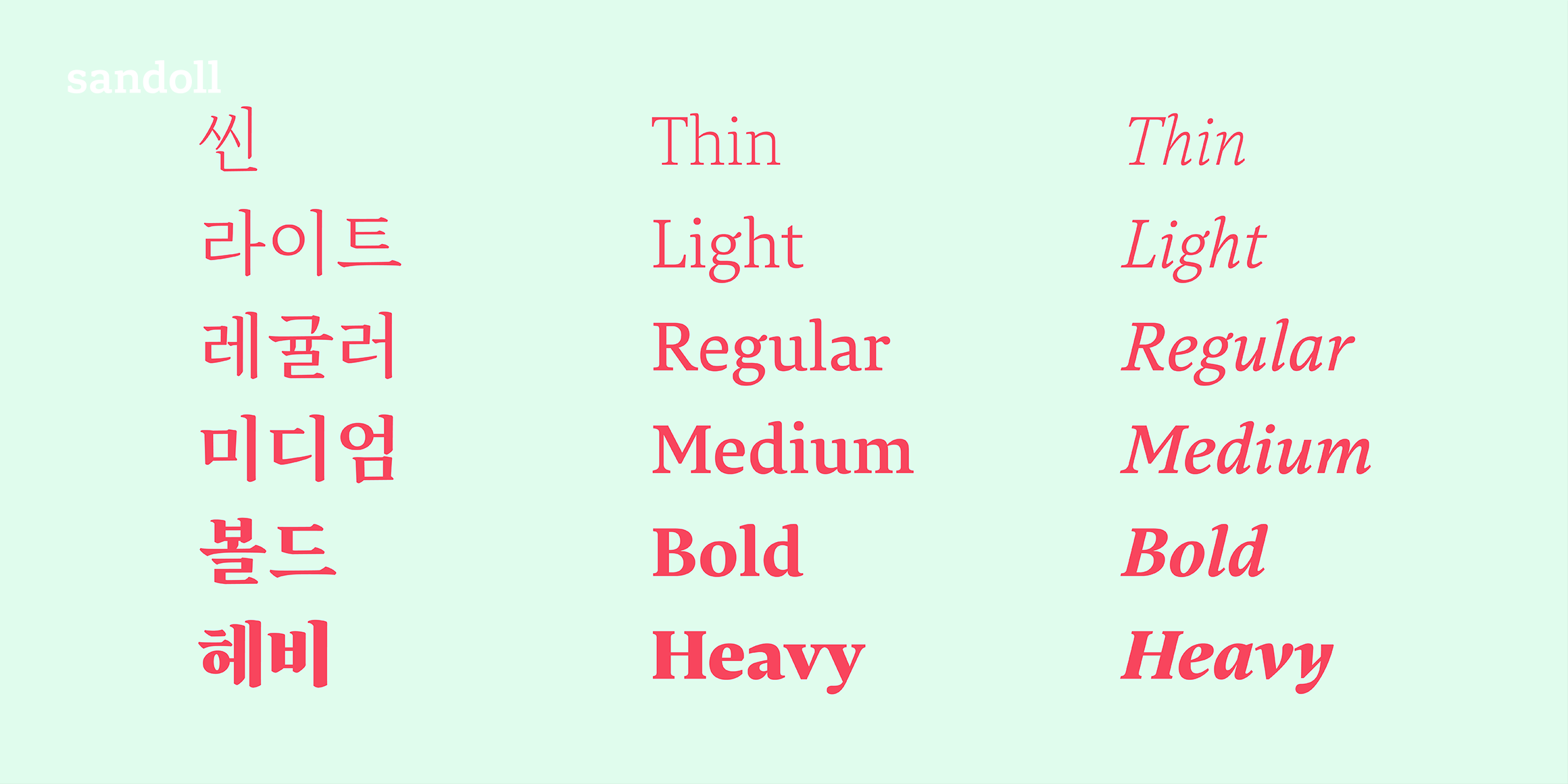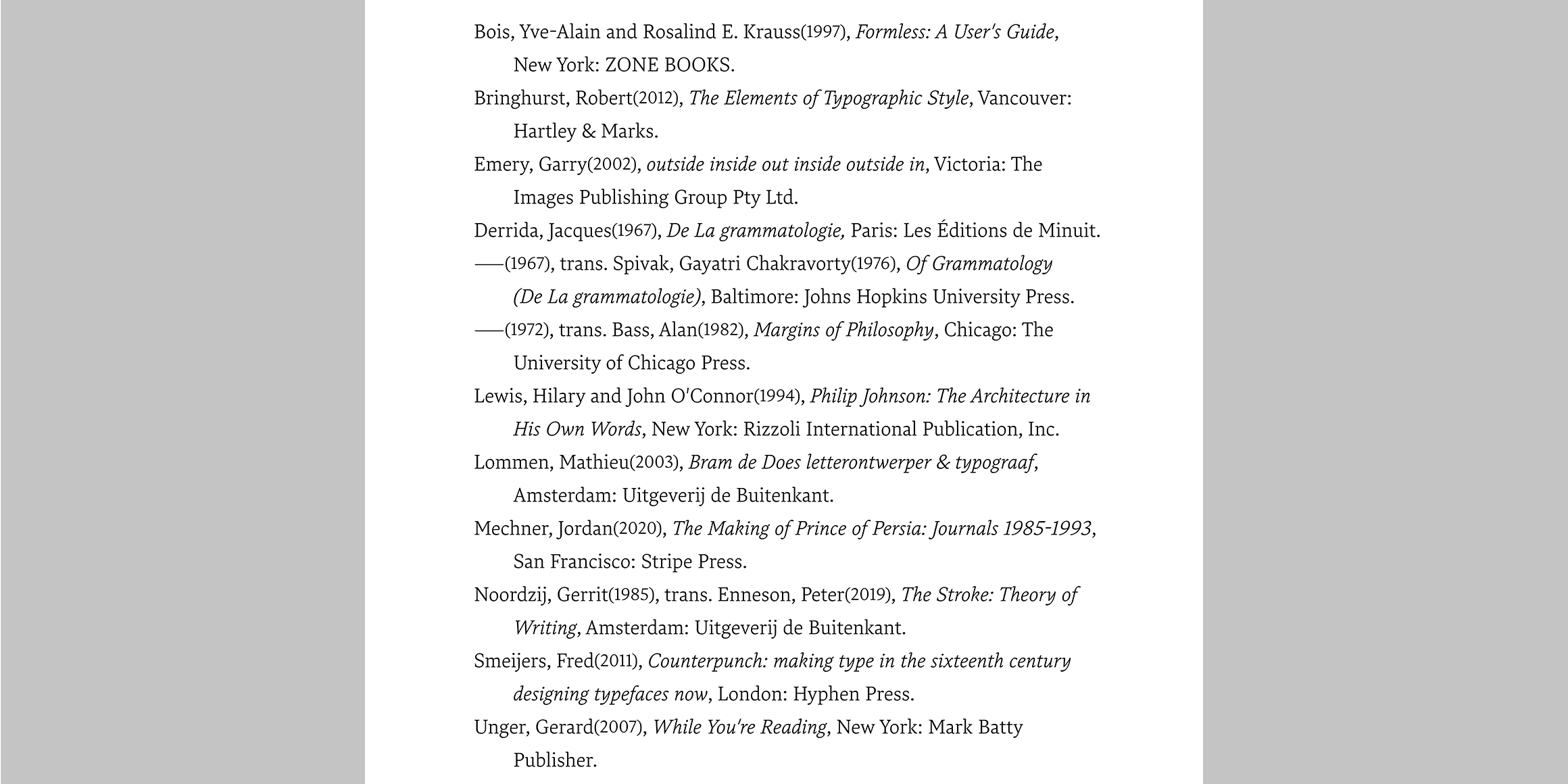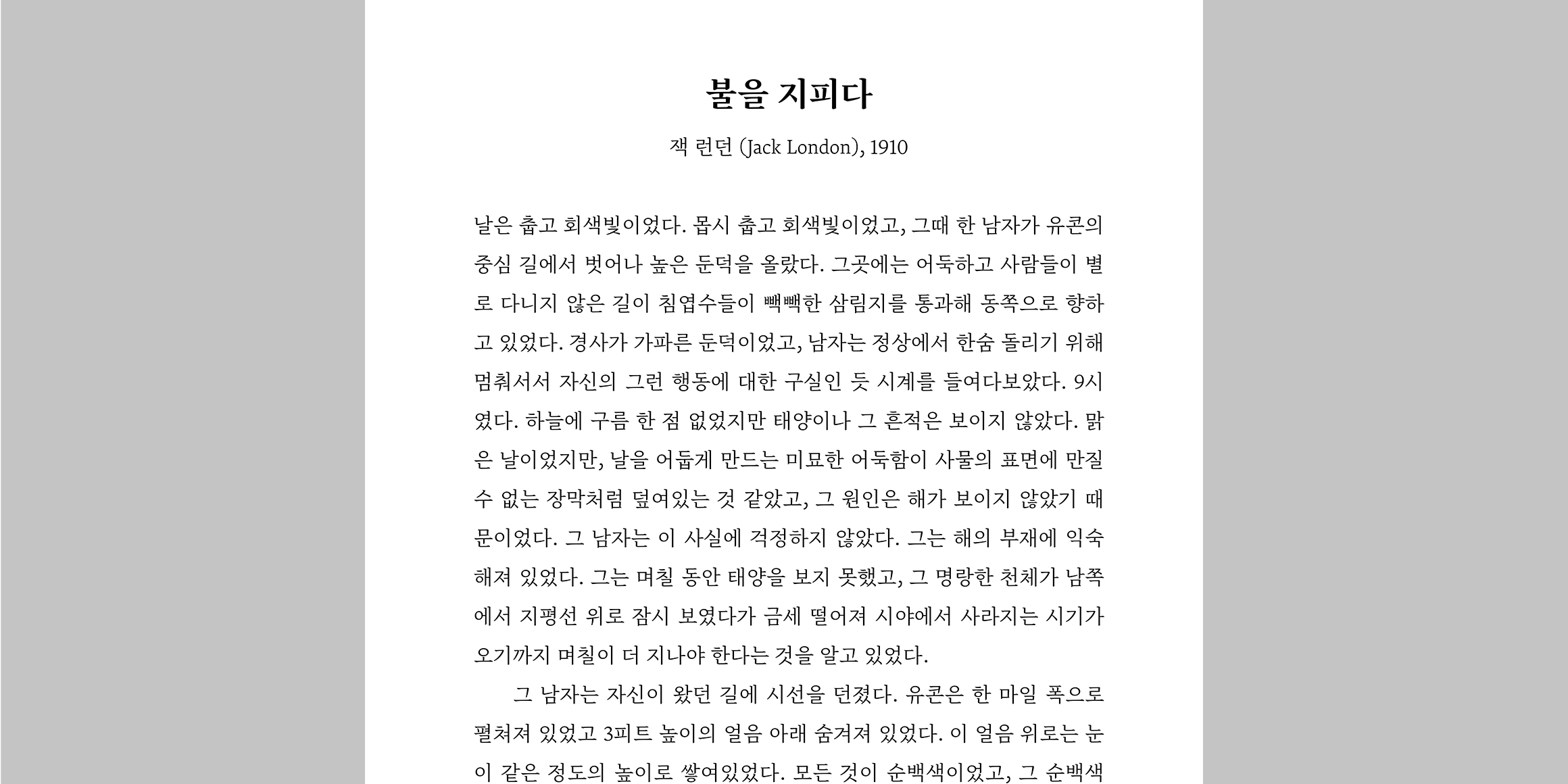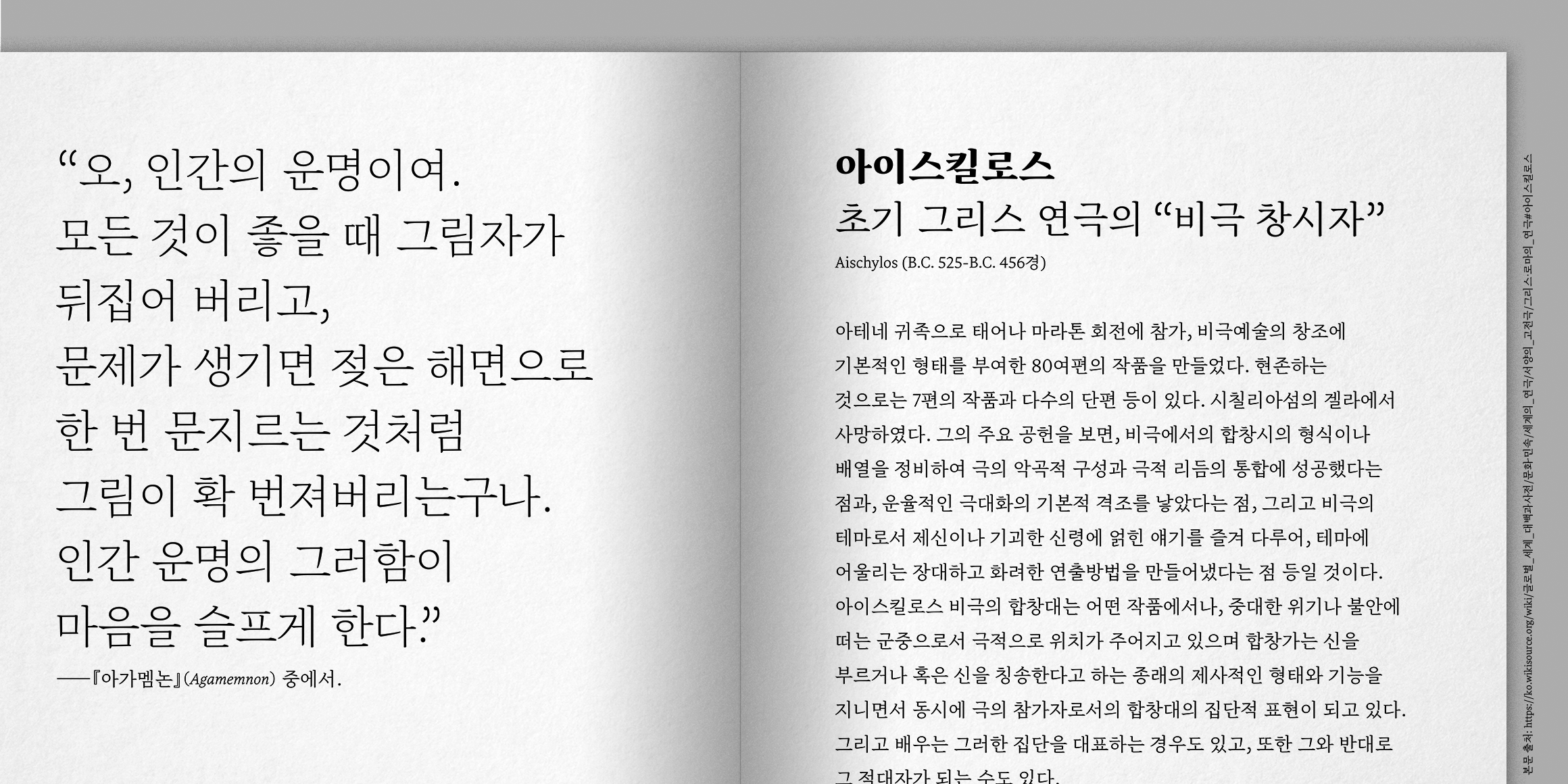
6개의 웨이트와 각 웨이트에 해당하는 이탤릭이 있고 쓰임새에 따라 골라 쓸 수 있습니다. 9-10pt 정도로 많은 글을 오래 읽어야 할 때는 ‘Lt(Light)’ 웨이트를, 24pt 이상의 제목이나 짧은 글에는 ‘Th(Thin)’, ‘Bd(Bold)’, ‘Hv(Heavy)’ 웨이트를 사용하시면 다양한 글을 일관된 분위기와 안정적인 가독성으로 포괄할 수 있습니다. 「SD 라바」의 디테일은 디지털 디스플레이에서도 긴 글을 편안하게 읽는 경험을 지향합니다. ‘Lt’나 ‘Rg(Regular)’로 편안함을 느껴보시고 ‘Th’, ‘Bd’, ‘Hv’로 포인트를 잡아보세요. 이탤릭을 사용하면 웨이트 변화 없이도 강조, 제목 표시 등의 정보 구분을 하기 쉽습니다.
「SD 라바」를 디자인하며 특히 신경 쓴 부분은 글자의 사이사이에 흩어져있는 흰 공간을 균질하게 배분하는 것이었습니다. 웨이트가 달라지더라도 같은 인상을 유지하도록 했고, 웨이트마다 가장 자주 사용될 크기를 기준으로 공간을 조정했습니다. 이런 이유로 본문용 웨이트인 ‘Lt’의 한글은 글자 너비가 같고, 나머지 웨이트는 조금씩 다릅니다.
「SD 라바」는 네덜란드 폰트 회사 티포텍과 협업해서 만들었습니다. 산돌은 한글을 디자인했고 티포텍은 라틴 문자뿐 아니라 그리스 문자, 키릴 문자를 포함하는 유럽 전역에서 쓰는 문자를 모두 디자인했습니다. 「SD 라바」는 모든 유럽의 언어를 정확히 표기할 수 있습니다. 또한 한글과 함께 많이 쓰이는 문장부호를 따로 디자인하여 추가했습니다. Adobe InDesign의 문자 패널 언어를 한국어로 변경하시면 사용할 수 있습니다. 이외에도 인디자인, 포토샵이나 일러스트레이터와 같은 Adobe 프로그램에서 합자, 작은 대문자, 숫자 (고정 폭/가변 폭, 라이닝/고전 스타일), 분수, 첨자 등 다양한 추가 기능을 선택할 수 있습니다.
「SD 라바」는 읽기 좋고 보기 좋으며 쓰기도 좋은 현대적인 다국어 세리프 폰트 패밀리를 의도했습니다. 여러분도 그렇게 느끼실지 궁금합니다.
*「SD 라바」 이탤릭은 라틴, 그리스, 키릴 문자만 지원합니다.
*Adobe 프로그램에서 라틴, 그리스, 키릴 문자가 적용되는 언어를 선택해서 사용할 때, “모두 대문자” 기능을 선택하면 괄호(parenthesis, bracket), 하이픈(hyphen), 줄표(dash), 쌍점(colon)이 기본 숫자, 라이닝 스타일 숫자, 대문자 높이에 맞게 바뀝니다. “문맥 대체” 기능을 선택하면 하이픈, 줄표, 쌍점 뒤에 라이닝 스타일 숫자, 대문자가 올 때 하이픈, 줄표, 쌍점이 라이닝 스타일 숫자, 대문자 높이에 맞게 바뀝니다. 기본 숫자는 라이닝 가변 폭 숫자와 디자인이 동일합니다.
*「Sandoll 라바」에서 오픈타입 기능 중 스타일 세트 7번으로 포함되어 있던 “Keep ẞ in small caps” 기능은 일반적인 목적의 폰트에는 필요하지 않아서 「SD 라바」에는 포함되어 있지 않습니다.